版式编排中的王炸技巧,带你领略“线”的魅力
今天我们要探讨的主题是版式设计中的线,相较于字体和图片来说,线给我们的印象或许并没有前者来的那么强烈,可这并不能成为我们忽视它的理由。作为版式设计中的基础元素之一,线的加入不仅能带来一定的装饰效果,更能起到调节版面的重要作用。 但问题是,你真的了解线条吗?当你在编排一个版面时,你能够准确的说出自己加线的目的是什么吗?如果你还在为版面中零散的元素而发愁,那么我相信,本期的内容一定会对你有很大帮助。那么接下来我们就把目光聚焦到这个不起眼的线条上,一起去探索一下关于线的秘密吧。
那么在开始之前,我们先来梳理一下什么是线,看看从线的定义上,我们能得到哪些信息。
线是一个抽象的概念,它开始于一个点,随着点的移动轨迹,我们就看到了一条虚线。
线也可以是任何形状,比如一排文字,就可以被我们看成是一条虚拟的线段。而随着点的轨迹越来越密集,我们最终就看到了一条实线。
线不仅有角度上的变化,同时也具有指向性的功能。不仅如此,线还有材质和长短上的差异,通过改变这些属性,我们就能得到各种样式的线条了。随着线条粗细的改变,我们对它的心理印象也会变的不同。时而粗壮有力,时而纤细轻盈。当然线条的轨迹也并不一定就是笔直的,当线条弯曲时,还能勾勒出各种变化丰富的造型。
当然线也具有很多错视现象,有时候,我们明明看起来是倾斜的线,实际上,它们却是水平的。
而有时候我们看起来是水平的线条,更换另一个视觉环境时,看起来又会变成弯曲的样子。
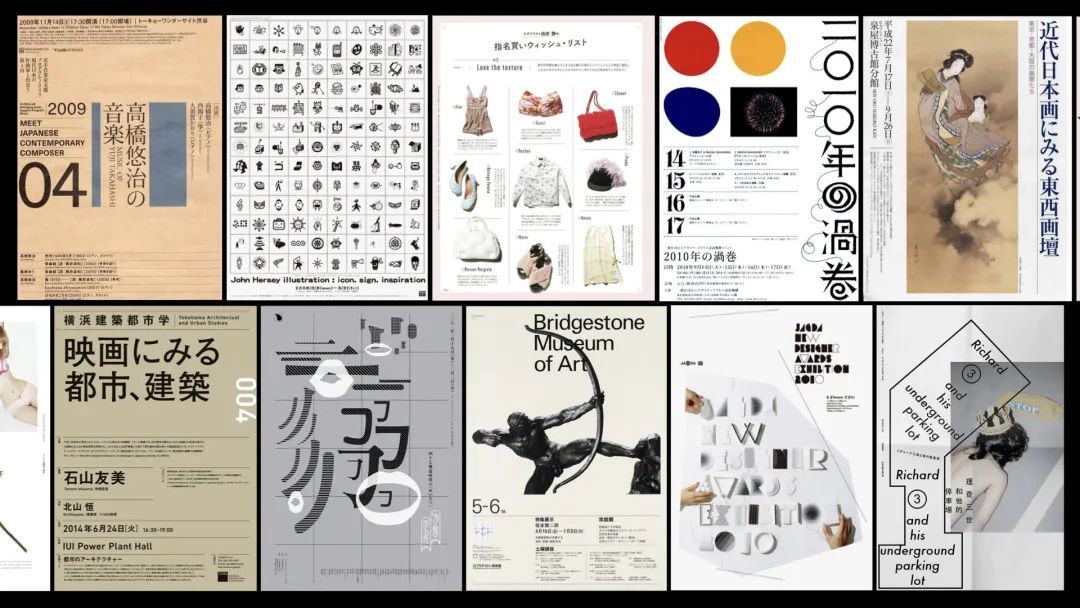
而在众多的形态中,几何外形的直线条则是最常见的经典样式,它在实际的版面编排过程中,起着至关重要的作用。
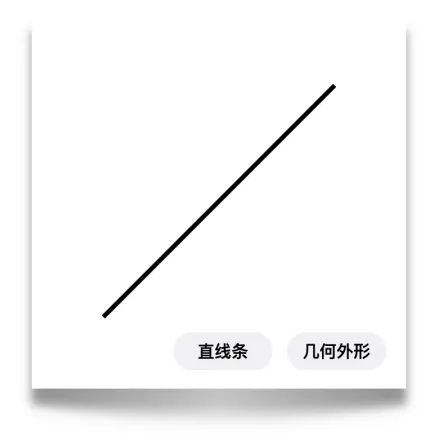
那为了更好的挖掘“线”的设计思路,我们这篇教程,就把目光锁定在更有实用价值的几何直线上。
那么通过前面的分析,我们对线条的定义已经有了一个初步的认知了。同时呢,我们也找到了版式设计中最常用的线条样式,那就是几何造型的直线。因为这类线条在造型上和字体更加接近,而且直线的轨迹也明显更容易绘制出来,所以这样的线条样式,我们经常能够在设计作品中看到它的身影。图片和文本内容通常来说都是不可以随意在增加的,但线元素就没有这种限制,那么线条的加入能够为版面带来哪些作用呢?
那么接下来我们就从线的作用切入,一起去探索一下线对版面都有哪些影响吧。
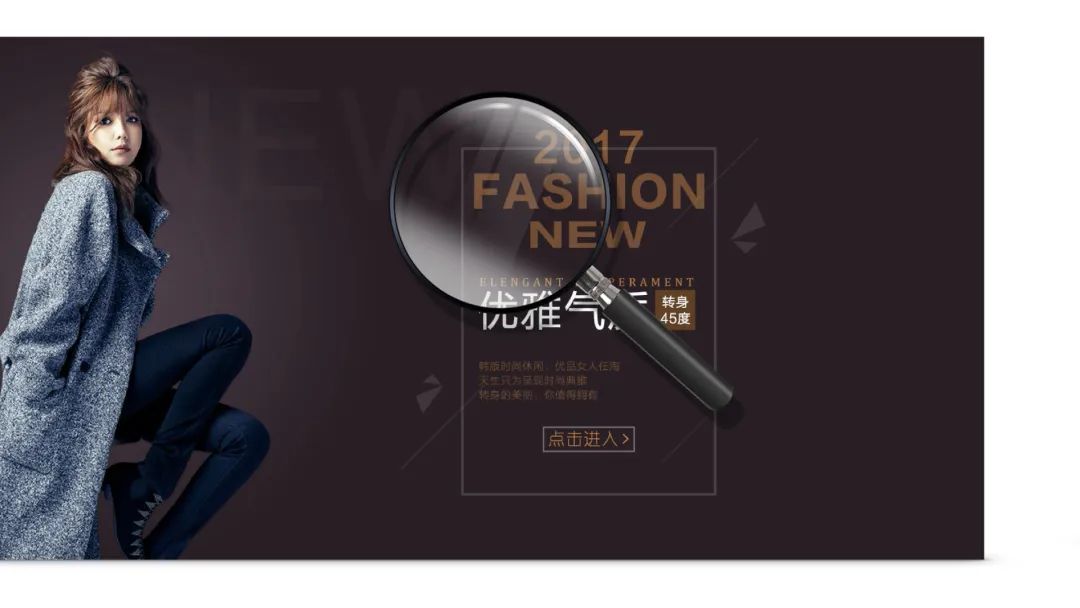
我这里搜集了一些运用了线的相关反例,试想一下,我们添加线条的时候,是抱着怎样的目的去设计的呢?通过这些并不成熟的案例,我们或许能够找出大家普遍存在的问题。比如我们现在看到这个版面,线的加入并没有产生什么实际的意义,反而扰乱的信息周围的空间,周围的倾斜线条也让人摸不着头脑。
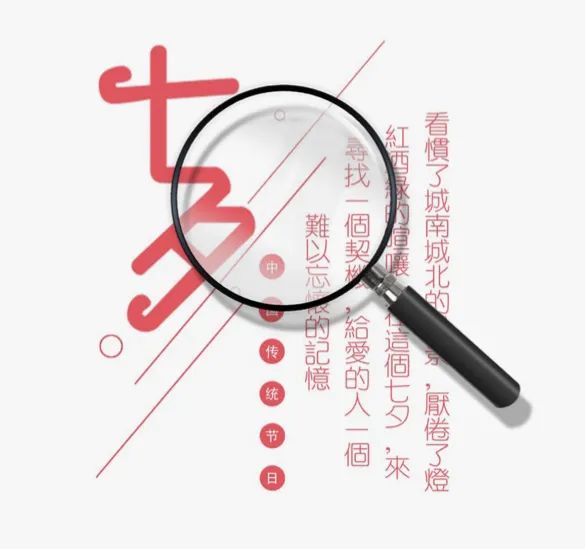
我们在看这个例子,也同样是加入了一些几何造型的倾斜直线,那么它添加线条的目的是什么呢?这里我的判断是,大家可能想通过这样的线条为版面添加一定的装饰效果吧。
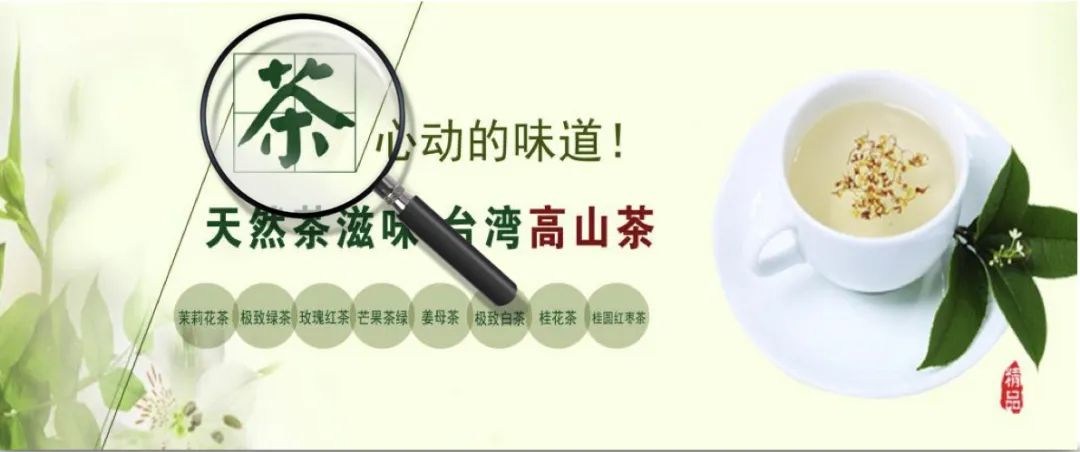
线条的加入的确能够为版面带来一定的装饰属性,但显而易见的是,这样的装饰感好像并没有解决美感的问题。反而会有些扰乱内容的嫌疑。
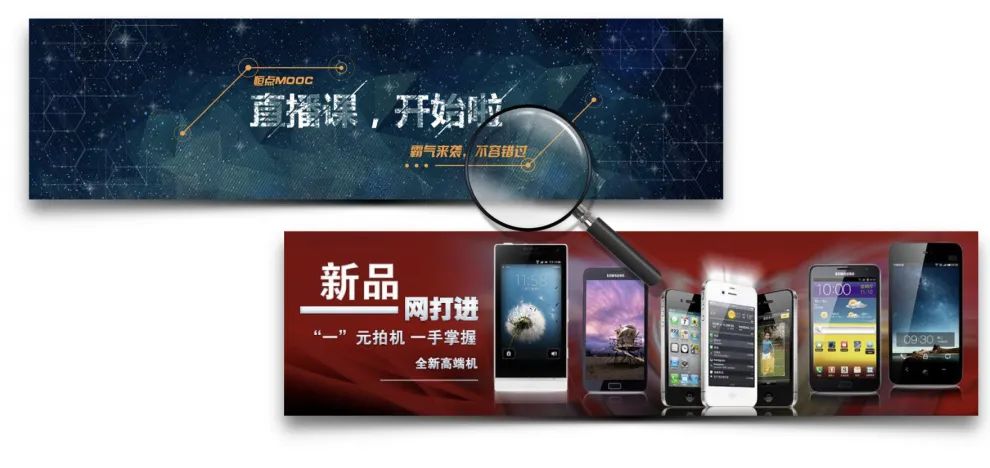
咱们在看这两个例子,还是能够很明显的看出来,这两个版面中的线条,好像也没有太过明确的功能性,仅仅是作为装饰出现在版面里。
所以盲目的在版面中添加线条是不会解决实际问题的,我们在学习优秀作品的同时,不仅仅要看到作品的表面美感,更要学习隐藏在其背后的思维逻辑。
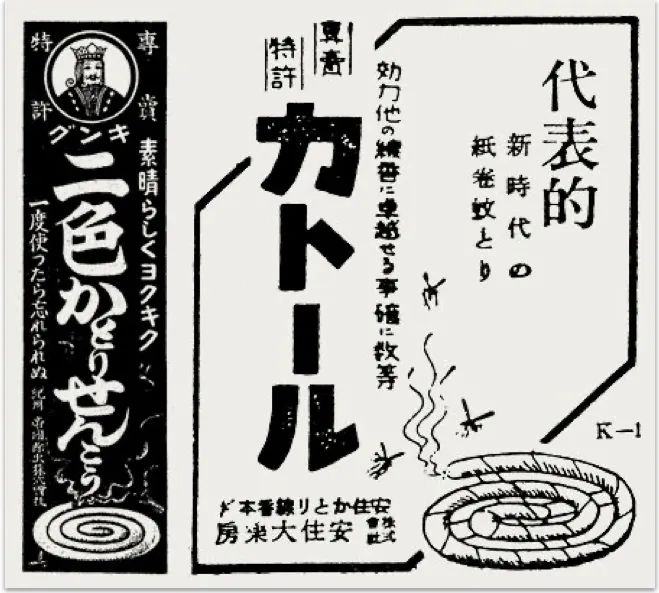
那我们怎样才能直观的找到线条的功能作用呢?我们可以试着逆向思考这个问题,如果去掉线条会怎样?
那么当我们把这个版面中最醒目的线框去除之后,会发现,元素之间的关联性变弱了,我们可以把修改前后的两个画面做一个对比,你发现了吗?去除线体之后,左侧明显会给人更凌乱的印象,而右侧添加线条后,明显变得规范了很多。
我们再来看这两张海报,能看到有哪些不同呢?左侧失去线条的版面,元素之间变的更孤立了,而右侧加入线条的版本,就显得更有整体性。
那看看这个版面,线条又起到了什么作用呢?左侧的版面虽然没有什么问题,但在使用线条分割信息之后,粗壮的金线,明显让男性的阳刚气质变的更明显了。
大家再来看一下这两张版面给人的第一印象是什么?左边的版面由于留白较多,会更安静典雅一些。而右侧加入线条的版本,粗壮的线条明显让标题变的更醒目了,同时在视觉重量上,也会显得更加平稳一些。
那么通过刚刚的分析,我们知道了线不仅仅只是装饰元素,它在版面中是具有实际作用的,那么什么时候可以加线呢?线又具有怎样的特殊属性呢?那么接下来我会详细为大家讲解。
线条本身就具有很多功能属性,如果一股脑的介绍给大家,相信一定会让不少朋友听的云里雾里,所以我决定把这些属性拆解开。
我们首先要讲解的是区分属性,说道线条的分割,这个概念大家应该不难理解吧。
那接下来咱们一起看看,在一个版面里,我们可以有多少分割的形式呢?首先最容易想到的,应该就是贯通版面的分割形式了,从画面从边缘开始,直到另一个边缘结束。
那么除此之外,我们还可以让线条的边缘从版心开始分割,这样线条就和其他文字信息一样,对齐在版心内部了。
咱们还可以把前两种手法做一个结合,这样就产生了半个贯通版面的分割样式。
咱们在换一种手法,线还可以对齐到元素的边缘。
首先,咱们可以尝试组合“贯通版面”和“对齐元素”这两种分割手法。第一步分割之后,咱们要做的就是确定好人物照片的位置。
随后,安排主标题信息,以第二个字为基准,绘制一条对齐线,然后把其余的内容安排在一条对齐线上,最后安排底部的文字信息。那么这个小画面也就编排完成了。
接下来咱们在做一版“半贯通版面”与“对齐元素”这两种分割手法的版面。首先,我们找到版面的中心位置,然后在右侧空间里绘制分割线,末端可以直到突破出版心之外。那么接下来,就是将标题内容和线条一样,对齐到版面的中线上了。
那么最后呀,我们把其余的说明内容,安排在版面的下方,那么这个小版面就规划完成了。
咱们再来做一版,分割线条“对齐到版心”的样式吧,同样也是和“对齐到元素”分割线,进行一个组合使用。
首先我们在背景中绘制两条不同粗细的线条,注意这里的线条末端是对齐在版心内部的,那么接下来,咱们把标题部分安排在左上方的空白位置上。
最后,把更小的信息,填补到另外两个空白处,这个版面也就完成了。
那么除了刚刚提到的方法呢,其实还有一种表格类型的分割技巧。一个完整的页面会被线条划分成多个更小的区块,这种手法特别适合用在那种·些内容很丰富的版面上。
这是一个内容很丰富的杂志页面,其中有很多组独立的内容,这就很适合采用表格类型的线条分割。
当然这种线条的划分,它同样是可以做出很多变化的,比如运用我们刚刚学到的内容运用“全贯通”样式的分割线,让每条线都分割到页面的边缘。
或者规范一个版心区域,让线条划分在一个范围里。
放出顶部的标题部分,只框选其中一部分内容。或者改变横向的线条,变成”对齐元素”的分割样式。
再或者说,放大其中一个元素,打破表格内部均等的状态。
那么接下来,咱们说一说线的引导属性。
这个场景想必大家都不会感到陌生了,悬疑电影中为了方便推理,常常会用线把有联系的人物、时间或地点用线连起来。这也是运用线条进行引导的一个有趣例子。
线条的引导属性大致可以分成两种方法,分别是由多个点之间的相互链接,以及从单个点向外扩散。
我们可以通过画面中的这两个案例,来体会一下这两种方法之间区别。我们可以明显看到,左侧的线条是链接了多个标题内容的,而右侧的线条,明显是从手为中心,在介绍手的各个部位。
咱们首先看看现在这个画面,假设我们都不认识鸭子,那么下方的描述文字就很难让我们理解它们所指的部位在哪了。所以在这种情况下,我们就需要利用线的引导属性了,采用单点扩散的方法,就是一个不错的选择。我们看,像这样把鸭子作为中心要素,周围的所有信息都围绕着它进行解说。是不是一下子就变的简单直观了呢?
接下来我们在试着做一个多点链接样式的版面,同样也是利用了线的引导属性,首先我们把文案信息安排在页面的顶部,竖向编排。
我们之前也提到过,文字也可以看成是一种虚线,所以,利用新加入的英文,也是可以产生分割作用的。最后,运用几何外形的斜线,把左右两边的文字进行一个链接,这样主标题部分也就刻画完成了。接下来就是补全其余的版面信息了,首先在下方我们置入一个瓷器。
随后在左下方安排展览的地址等信息。右下方的部分,安排这个展览的副标题。最后添加对于的颜色,那么到这里,这个版面也就设计完成了。
那么接下来,咱们来聊一聊线的填充属性。
有些时候,我们把所有的文案都放到版面里,画面还是会给人很空的感觉,那么这种情况下,我们就可以利用线条来填充这部分空间,因为不同于图片和文案,线条并不承载任何信息,所以对于线的运用是不会有限制的。那么新的问题是,我们要怎样填充这部分的空间呢?
运用网格就是一个不错的选择,我们并不需要用线填满每一个缝隙,只要缩小划分后的区域范围就可以了。这样的方法不仅能让空间看起来更饱满,同时也达到了增强视觉面积的作用。
除了网格,我们还可以继续精简线条的数量,倾斜的线条,就能带来更强的体量感,它能够让一个区域看起来被占据,又不会让整体版面看上去很拥挤。
咱们来看这两个实际的案例,左侧是运用了网格去填补空间的例子,而右侧则运用了更加精简的倾斜线条,同样也达到了填补空间的目的。通过强调线条的部分,我们能更清楚的看出这两个版面中线条的分布情况。
在这个版面里,我们即使把字放到最大,其实也只能占据二分之一的面积,在这种情况下,线条的填充就是一个很有效的方法。这里我使用了更加精简的斜线,填充在对角线的空白位置上。
接下来我们把主视觉安排在文字的上方,形成图叠字的样式。这是一组间距相等的信息,虽然排的很整齐了,但阅读的时候还是会容易串行。让一部分元素叠压在图片上,通过这样的方式可以增强版面中的层次感,那么最后,在空白位置上,我们加入其余的文字信息,这个版面也就完成了。
文字的笔画,其实也可以被看成是线条,通过延长文字的笔画,我们同样能够激活线的填充属性。就像画面中的这三个案例一样。
我们看,虽然这三个版面拉伸的方法并不相同,但实现填充留白的方向却是一致的,我们可以记住这种处理手法,等到我们遇到了合适内容的时候,就可以尝试这利用这种手法去刻画主形象了。
我们这里选择了一个笔画结构相对简洁的英文作为基础,我们看它的笔画有哪些可以做拉伸处理呢?
X的这一笔就看起来很有空间感,那么其余的笔画呢?接下来咱们试着拉长字母N的笔画,虽然文字的笔画被拉长的,但是我们依然可以辨认出它们来。那么为了尽量保持变化规则上的统一,我们把同样是笔画朝向外侧的字母t也做一个拉长的处理,那么到这里,这个小画面就差不多完成了。
那么接下来咱们说一说线的强调属性。
如果一个版面中只有一部分文字带有线条,那么这个反差的部分就会被其余元素所对比出来,这也就产生了强调的作用。我们大家应该都有在书本上划线的经历吧?这种对内容的加工,虽然简单,但也很有效果,它能够很轻易的产生凸显信息的作用。
咱们一起来做一个画册的对页,首先我们确定好页面的中心以及版心的大小,我们先确定好图片的部分,这里我把两张照都安排在版心的内部。随后为了增加一丝变化,我这里将左侧页面的版心部分划分出一个更小的区域用来安排页眉与标题信息。随后在右侧的区域中划分出双兰,并安排好其余的信息内容。
我们把网格隐藏掉,看一下最终的效果,那么到这里就结束了吗? 当然没有,咱们还没强调内容呢。
我们可以选择强调这段引言文字,因为通常引言都会代表一段内容的核心思想,所以强调这部分从功能性上说也是可行的。那么我们使用红色的线条来强调这段信息。
即便缩小观看,这段文字也是很抢眼的对吧,那么这个例子到这里也就设计完成了。
那么接下来我们聊一聊线的关联属性。
那么线的关联性是怎样产生的呢?我们拿画面中的这两排人举例,如果我想让他们其中一部分人相互产生关联的话,要怎么去做呢?很简单,只需要让他们带上相同的帽子就可以了。
同样的,我们可以把这个元素替换成线,比如这个版面,在每一段文字上方都被添加了线条,这样就形成了一种呼应关系。
咱们把线条凸显出来看,是不是就更明显了呢?当所有文字都带有线条时,那么这几段文字就具备一定的关联,那么如果只有一段文字是带有线条的呢?那它就变成强调属性了对吧。
根据文案我们可以知道,这是一张和面包有关的海报设计。接下来我们在背景中加入对应的面包照片,这里一共有四块面包,我们选择造型更饱满的这张作为画面中的焦点元素。
在背景中,我们加入一些肌理,烘托高品质的氛围。黑色的背景也更容易把黄色的面包凸显出来。
接下来我们把把对应的文案信息安排在照片周围,按照层级划分字号的大小。
划分网格,并规范好文字组合的比例关系。
那么到这里,版面的基本结构就基本安排好了。最后我们可以在元素之间插入线条,让元素的构成显得更饱满一些。
到这里,这个版面也就基本完成了。面包周围的元素,由于被插入了相同的线条元素,也让它们之间的关联属性得到了增强。
我们可以对比一下,明显右侧加入线的版本会显得更有关联性对吧?
那么最后一个,就基本没什么悬念了,我们接下来就讲一讲线的图形属性。
线本身就是构成图形的基本元素,我们的文字也是从象形文字逐渐演变过来的,比如我们看右侧的这个网字,就看起来真的很像一张网。对比我们现在使用的汉字来说,图形感已经没有那么明显了,因为我们太熟悉它们的样子了,所以文字的印象就会格外的强烈。
如果我们想重新激活文字的图形属性的话,加入线条就是一个非常有效的方式。因为线条的加入能让文字看起来更陌生一些,我们看画面中展示的这些案例,是不是看起来都很有图形的感觉呢?
首先在这个画面里加入一段文字,然后呢,咱们来试着想一想,都有哪些添加线条的方法呢?一条线段,可以把它直接叠在文字上,这样也就打破了我们对文字的固有印象,图形的感觉自然也就被增强了。当然我们也可以把它像这样,直接安排在文字的下面。或者像这样上下各一条,形成一个包围的感觉。又或者让线条出现在左右两边,形成半包围的结构。等等各种装饰手法去激活文字的图形属性。
想不到线条有这么的多学问吧?作为版式设计中的重要组成元素,线条不仅能带来装饰性,同时它也具备解决实际问题的功能性。合理的运用线条,会让你的作品看起来更加出色。虽然创意是没有拘束的,但在面对阅读逻辑与传播效率时,线条的运用还是会有很多规则的。那么接下来我们就一起来分析一下线在版面中都有哪些需要注意的事项吧。
线条毕竟不能承载信息,所以大部分情况下,我们都要保证线条的视觉强度不能大于文字。所以区分主次是我们需要解决的首要问题。
基于这样的思考,我们看现在这个画面,是不是就很有问题了呢?那么解决这个问题的方法也变得很明确了。那就是降低线条的粗细。
我们可以让线条的粗细度维持在和文字相同的水准,这样从灰度上就能显得更加和谐与统一。
那么除了让线与文字和谐共处之外,我们也可以强调文字信息,通过降低线条的粗细和色彩,达到减轻线条视觉强度的目的。
除了区分主次,我们还需要让线条的出现,尽量不要干扰到文本信息。咱们看这个例子,虽然在线条中加入了很多装饰和变化,让画面看起来没那么单调,可这样的操作也占据了文本周围的留白空间。不仅增加了阅读压力,同时也让整个版面产生了很压抑,密不透风的印象。
针对这个画面来说,其实加线的必要性并没有那么大,我们只用留白其实就可以解决区分内容大问题。
如果一定要加入线条,我们也可以加入这种经过弱化的线,它的出现,仅仅是为版面添加一丝装饰性,并不会影响到内容的阅读。
或者,调整周围的留白空间,让线条的分割显得没有那么拥挤,这同样也是一种增添形式感的方式。
那么除了以上提到的两个方面,在运用线条的强调属性时,我们还需要注意一些问题。比如我们现在看到的这段文字,我们来尝试用线条去强调它里面的几个关键词。
你发现问题了吗?线条出现的位置问题,也会让我们观看时产生困惑。比如我们现在看到的,由于底部的两段文字距离线条更近。所以很可能会让人误以为被强调的是这两段内容,可事实上并不是这样。
那我们试着把线条居中摆放呢?可这样也会产生新的问题。那就是线条上下方的文字,都有可能被当成是被强调的信息。我们看,前两个内容还说的过去,可最后的这个明显就不是一段完整的句子了,这就很容易让人产生困惑感。
那针对这种只强调局部内容的情况,线条的强调位置,还是要尽量靠近文字的,这样从逻辑上也更加符合人眼的认知过程。人们会更容易理解被强调的内容,并且关注到它们。
到这里,相信大家已经对版面中线这个元素有了一个基本的认识了,无论是用来强调信息还是关联内容,线的加入总能让版面变得更有条理。那么为了便于大家的理解,接下来我们通过一个封面的设计案例,一起来巩固一下我们学到的新知识吧。
虽然把知识点拆开会更便于我们的理解,但真正在实际的运用过程中,这些线条的特点都是相互叠加的。所以最后咱们在通过一个完整的案例来一起梳理一下今天的内容。
在开始之前呢,我们先了解一下这个项目的背景,首先这是一个书籍封面的设计,书名叫《游戏改变世界》,是一本国外的著作。那单独看这个名字,可能我们会以为这是一本讲述某款游戏的书,或者是游戏的发展历史之类的内容。
而在详细的了解了这本书之后呢,我们会得到这样一些信息,“游戏化可以重塑人类积极的未来/改善生活,解决能源危机 /提供现实世界匮乏的奖励与挑战等等。 简单来说,这是一本分析游戏性,并且试图通过游戏的方式去解决现实问题的书。
所以在书籍的气质上,我们想把它定位在相对成熟与严肃的方向,但游戏本身的趣味性也是书籍的核心内容,所以我们也需要让这方面的属性有所体现。
在这本书里,还提到了关于游戏性的四个决定性特征:首先目标,就是指在一个游戏中,玩家想要达到的某个结果,这个结果可以说是吸引玩家投入并游玩的一个关键方向了。
对于游戏的第二个决定因素,就是规则,在一个游戏中,需要规定一个玩家能干什么和不能干什么,以及怎样去实现这个目标。
第三个是反馈,反馈系统是告诉玩家距离实现目标还有多远的机制,这也是激励玩家继续游戏的有力手段。
那么最后一个就是自愿性,它就是让玩家在了解了目标/规则和反馈之后,还有兴趣想要继续参与下去的动力了。
书里讲到的这种游戏性,其实也很适合体现在封面上,因为我们可以通过这一点呢,去呼应这本书的核心思想。可问题是,怎样才能在平面的媒体中展现出游戏性呢?
在视觉传达领域里,相信大家都知道,最重要的就是传达效率了,而相比较简单的强调信息来说呢,我觉得,让人们愿意去主动阅读才是更有效率的传播方法。
比如我们看这个标题本身就是由三个词组合到一块的,所以我们可以把它们再次拆解开,形成一个视觉上的引导。这样虽然增加了一些阅读上的障碍,但在解读的过程中,也会多出很多趣味性。
那么基于以上的思考呢,我最终决定在书籍的封面上与读者做一个视觉游戏,既然是要通过游戏改变世界,那么就干脆从每一个阅读封面的读者开始吧。
那首先为了让这个小空间看起来没有那么方方正正,我把标题拆解成了三份,分别嵌入到了这个方块里面。
根据阅读的逻辑,咱们按照Z字形的方向安排它们。左侧的角落我也添加了一个倾斜的切角,让图形的外观看起来能够更有变化一些。
紧接着呢,我在文字的周围做了四个开口,也是希望人们能够通过这种看不见的线条呢,去解读出标题的含义。那么这种想要解读出标题是什么意思的想法,其实就可以理解成是游戏性中的一个目标了。
那如果直接让视线就这样通过,那未免就太无聊了,为了增加一些游玩的乐趣呢?我准备在里面设置一些障碍和通道,形成一个迷宫的感觉。那么通过不断的尝试和推敲呢,最后啊,我就得出来这样一个迷宫的图形了。有了目标和规则之后,游戏性也就逐渐产生了。
为了增强这种规则性呢,我在入口和出口的地方,还设置了一个引导箭头,通过这样的暗示,让读者更容易明白这个游戏从哪里开始,和从哪里通关。那么接下来我们还要给读者设置一些反馈,我这里的通关礼物,就是改变世界的钥匙了,也算是一个小奖励吧。除此之外呢,在参与游戏的过程中,我们也能够知道自己的视线走到了哪里,并且也预判距离下一个关卡还有多远,这些都是正向的激励反馈。当然这里咱们还可以加入一些有意思的小东西,那就是当你的眼睛走到死路的时候,还会有一个小骷髅的标志。这或许是一个小敌人,或者是上一任探险者的骨骸吧,随你怎么去想。
那么到这里,这本书的主形象就刻画完成了,接下来就是余下的内容编排部分了。那么根据目前的这个构成情况来说,版面上方的大部分面积都是水平与垂直的线条,这虽然能够增加视觉上的稳定性,但也多少会有规矩和刻板的印象。如果下面也编排的很满。很规矩,那最终的版面一定会看起来很刻板。所以在下面的文字编排思路上,我决定选择留白空间更多,编排变化更活泼一些的版式结构。
那么首先,我们先大致确定好下方文字的字号大小和位置关系。在灰度上也尽量与上面的图形保持统一,不需要过度去强调它们。副标题的英文部分,在版面中的优先级并没有那么高,所以我们把它安排在靠右的位置上。更多的分栏也是增加结构变化性的一个有效的方式。
副标题的英文部分,在版面中的优先级并没有那么高,所以我们把它安排在靠右的位置上。更多的分栏也是增加结构变化性的一个有效的方式。那么主标题的英文部分,我们继续沿用这种视觉的引导,但这一次我们使用看得见的实线。那么在构成上呢,也可以让它有一种绕拍的感觉,这样倾斜的角度也能够与顶部的图形产生一个呼应。
那么除了引导之外,我们也可以利用线条的分割与链接的属性,去填补右侧空间多余的留白部分,同时这样的处理也能让组合看起来更平稳一些。结构处理好后,我们可以让其中相对更重要的标题与作者信息,看起来稍微有一些装饰性与图形的印象。这样会让它们看起来更凸显一些。
这里还有一个小细节,我们可以看仔细一些,现在我标注的这个部分,虽然没什么问题,但也缺少了一些灵活性。我们可以把这里稍微做一个角度上的变化,这样一来,细节部分会给人一种手工拼贴的印象,让整体看起来更活泼,我想用这种处理去抵消那种按部就班的刻板感觉。
那么最后呢,运用网格系统规范一下细节,这个版面也就差不多完成。
这个案例,我们运用了内容中反复提及的游戏性,让封面本书就成为一个视觉游戏,这样的设计能够让读者在翻阅之前,就能够体验到书籍的核心内涵。虽然我们都清楚,在游玩之前,当人们把这本书拿在手里时,其实就能够很容易的从外侧解读出标题含义了。但既然游戏已经摆在眼前了,我相信它也一定会引起你我的好奇心,去试着游玩一下的。那么有兴趣的朋友当然也可以暂停试一试,看看你能够快速通关吗?
那么在最后,我们一起来总结一下这期内容都讲了些什么吧,首先,我们一起探寻了线的定义,并且也知道了其中最常用的线条样式。那就是几何外观的直线条,通过对这种线条的应用与分析,我们一共得到了六种属性,它们分别是区分、链接、引导、强调、填充和图性感。每一种属性当然也都不是独立存在的,很多时候它们都是相互叠加的状态。也希望大家灵活的运用它们,千万不要去死记硬背。那么本期的分享内容就到这里,我是东宁,咱们下期见!